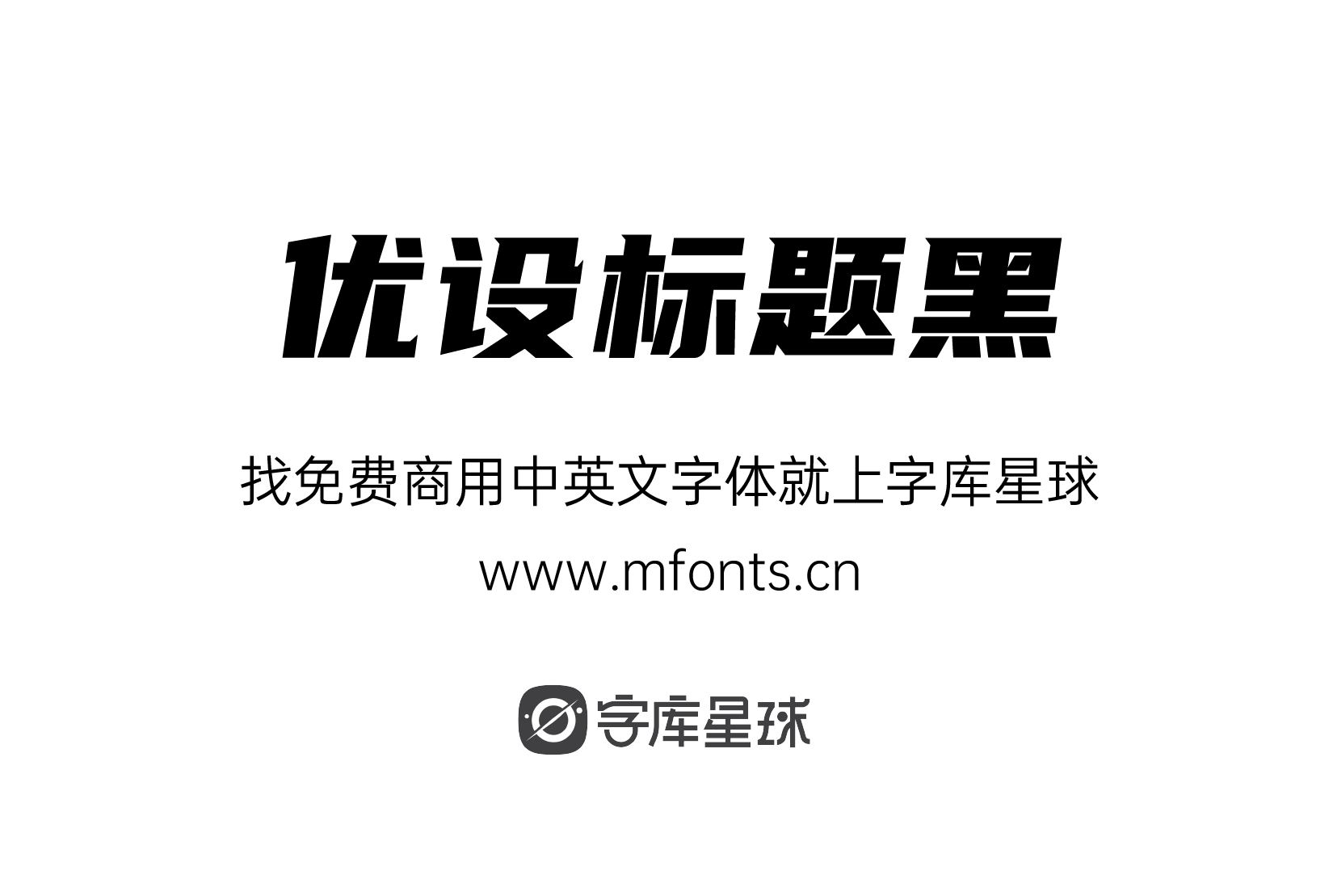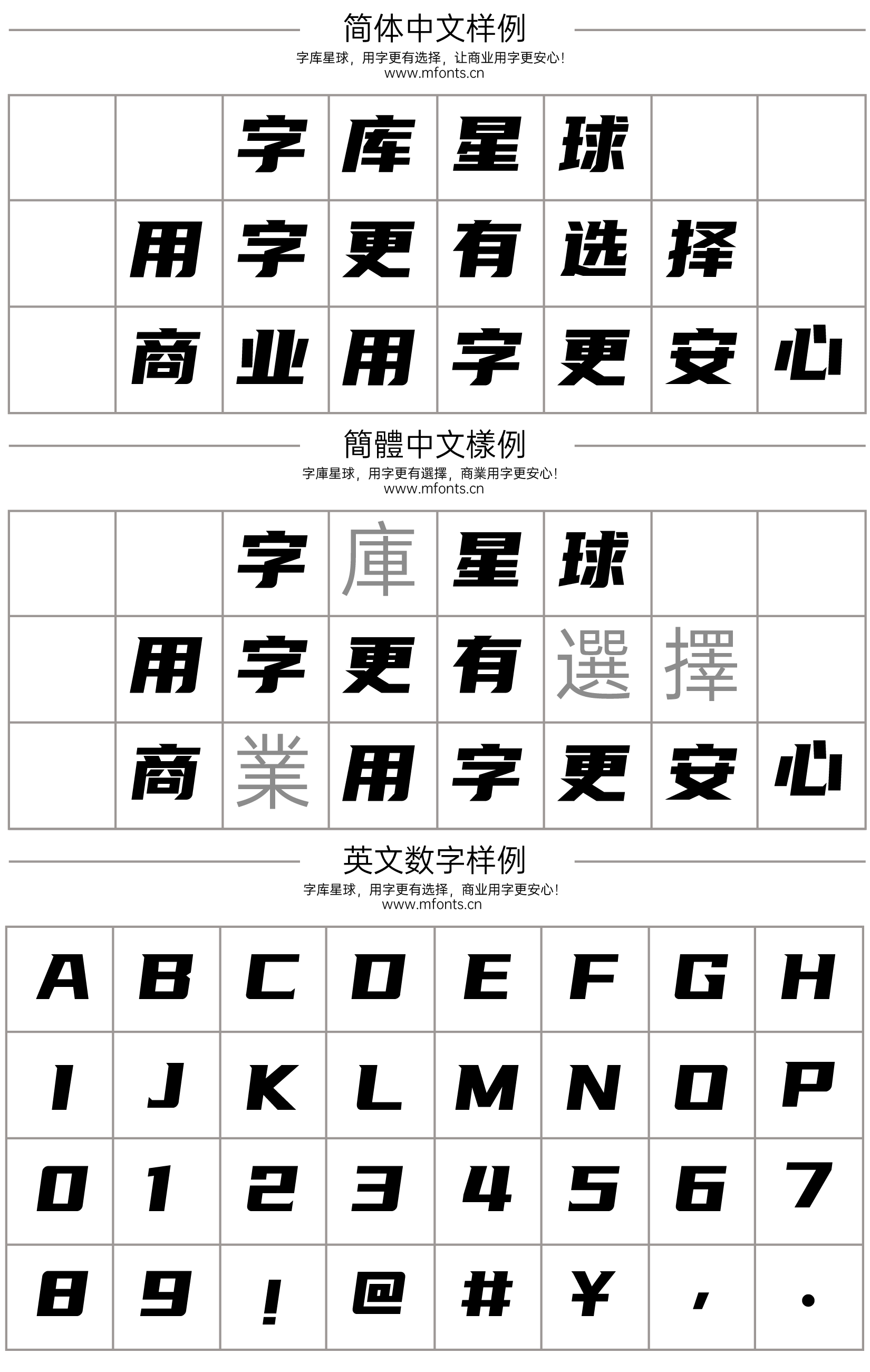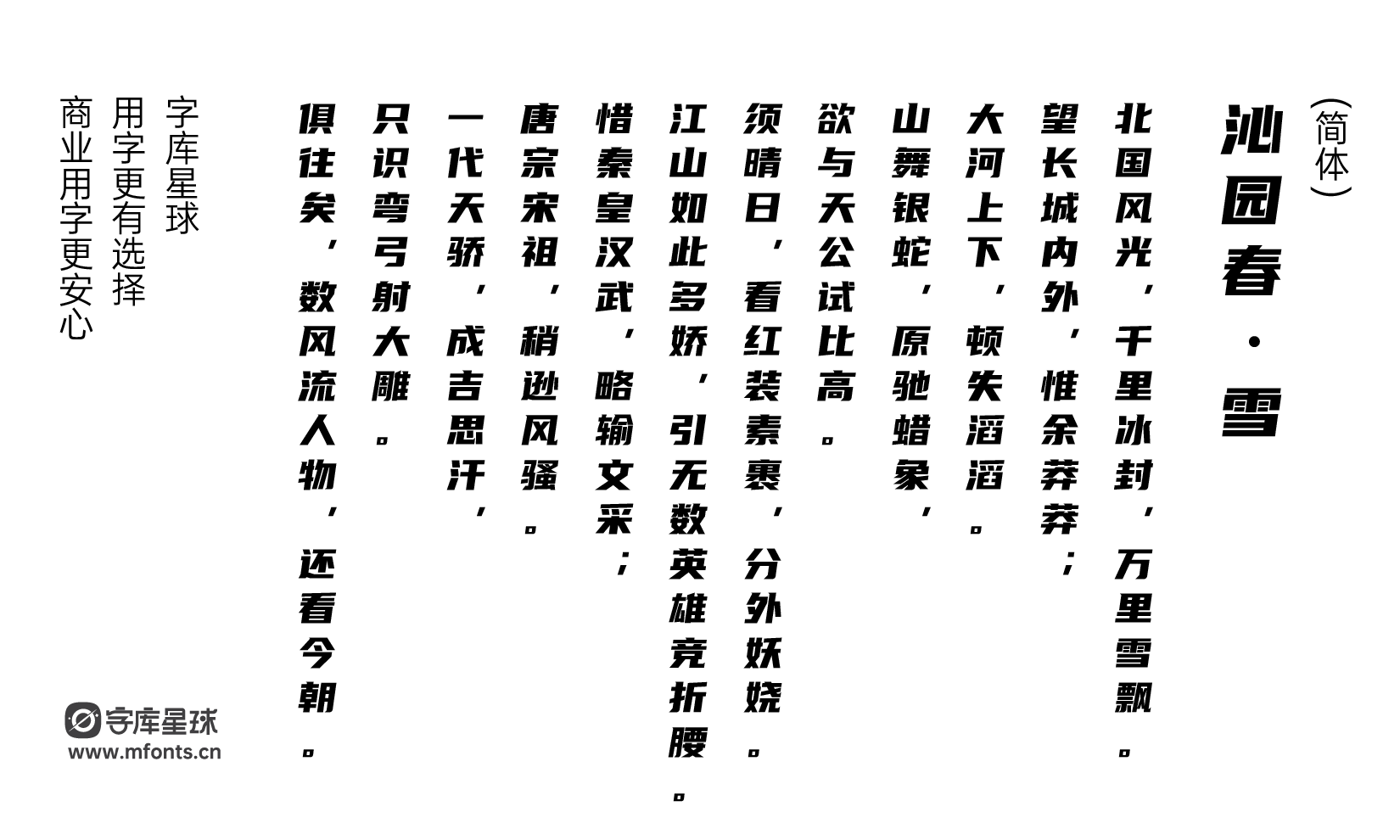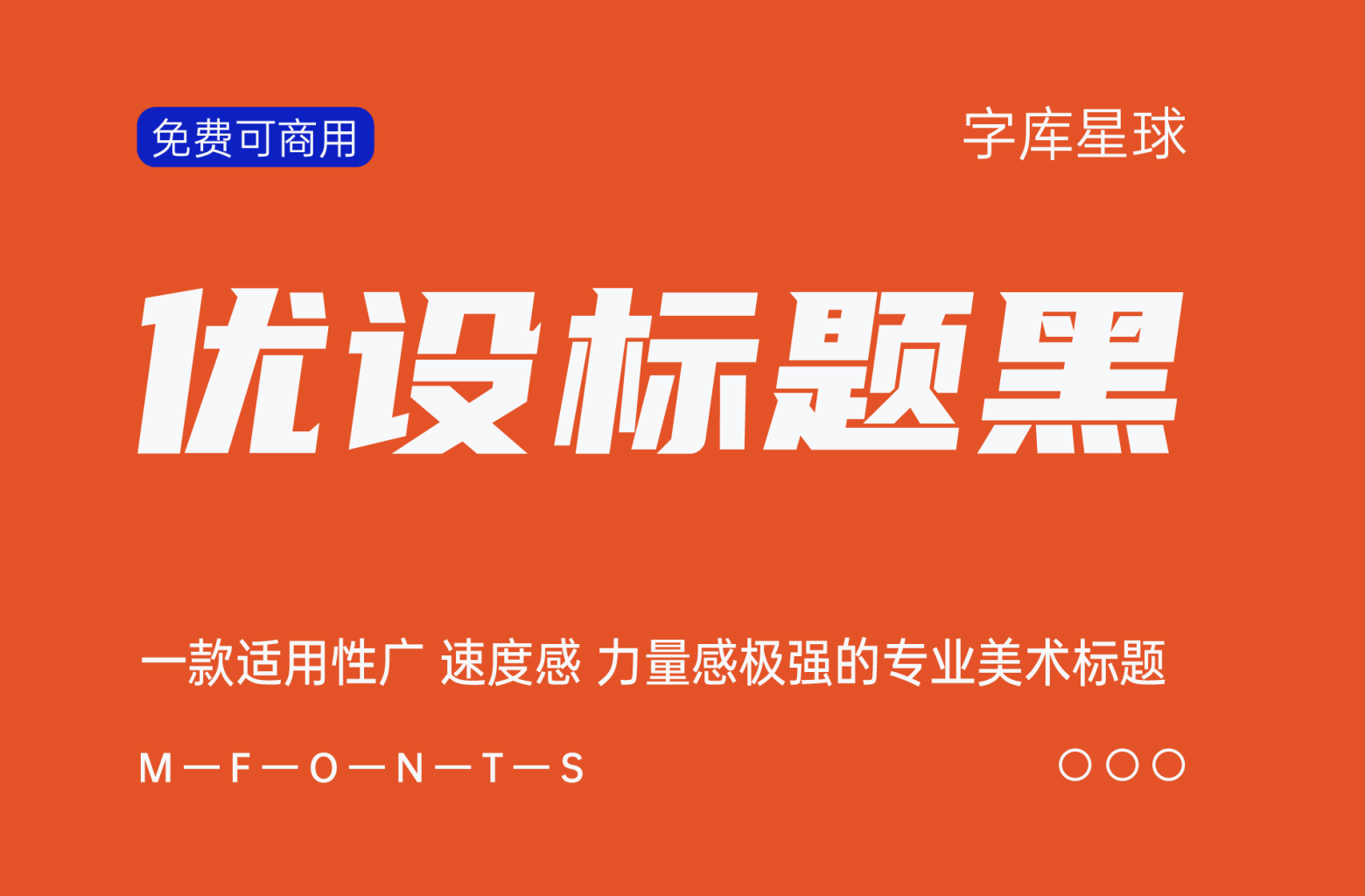
优设标题黑是一款适用性广,速度感、力量感极强的专业美术标题字体。
它以黑体字型为基础,整体字形沉稳,同时采用较大字面和粗壮的笔画来强化力量感。每个字体水平倾斜 8° 的设计,赋予了字体极强的速度感,为了让字体倾斜后也能保持稳固,设计师将整体字身设定宽扁。而起笔和弯钩上独具匠心的尖角设计,不仅突显了设计的几何感,而且方便后期修改。
所以这款字体,用在各类品牌广告和产品包装设计的标题上,最合适不过!
优设标题黑应用场景
文章标题:优设标题黑